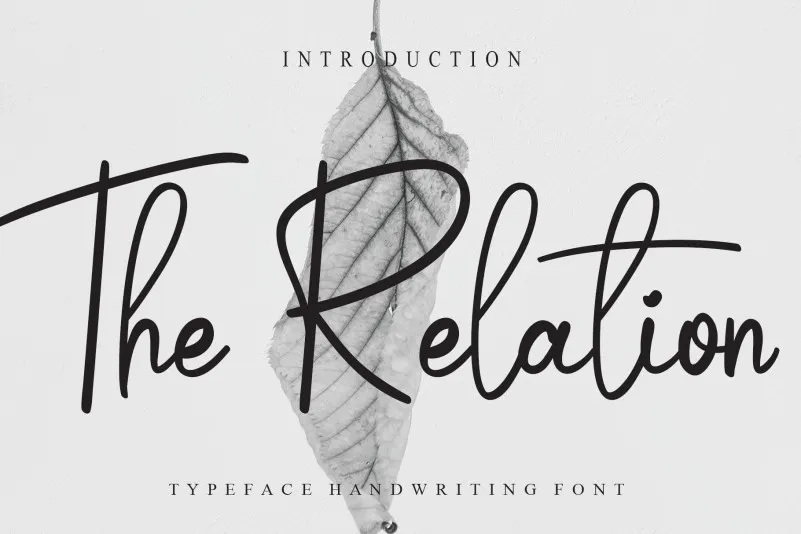
The Relation Script Font – Download Grátis
A “The Relation Script Font” é uma elegante escolha para quem procura personalidade em seus designs digitais. Criada pelo designer creativletter, esta fonte foi projetada para fornecer um toque único e divertido ao seu trabalho visual. Com traços fluidos que evocam a autenticidade de uma escrita manuscrita, é perfeita para criar mensagens que se destacam em sua página. Ideal tanto para uso profissional quanto pessoal, esta fonte oferece um equilíbrio entre seriedade e originalidade. Seja para marcas ou textos legíveis, a “The Relation Script Font” proporciona uma experiência visual única e intrigante, garantindo que você sempre seja notado no meio de sua comunicação digital. Sua versatilidade permite adicionar um toque autêntico a qualquer projeto, seja em cartões de visita, projetos gráficos ou até mesmo em design editorial.